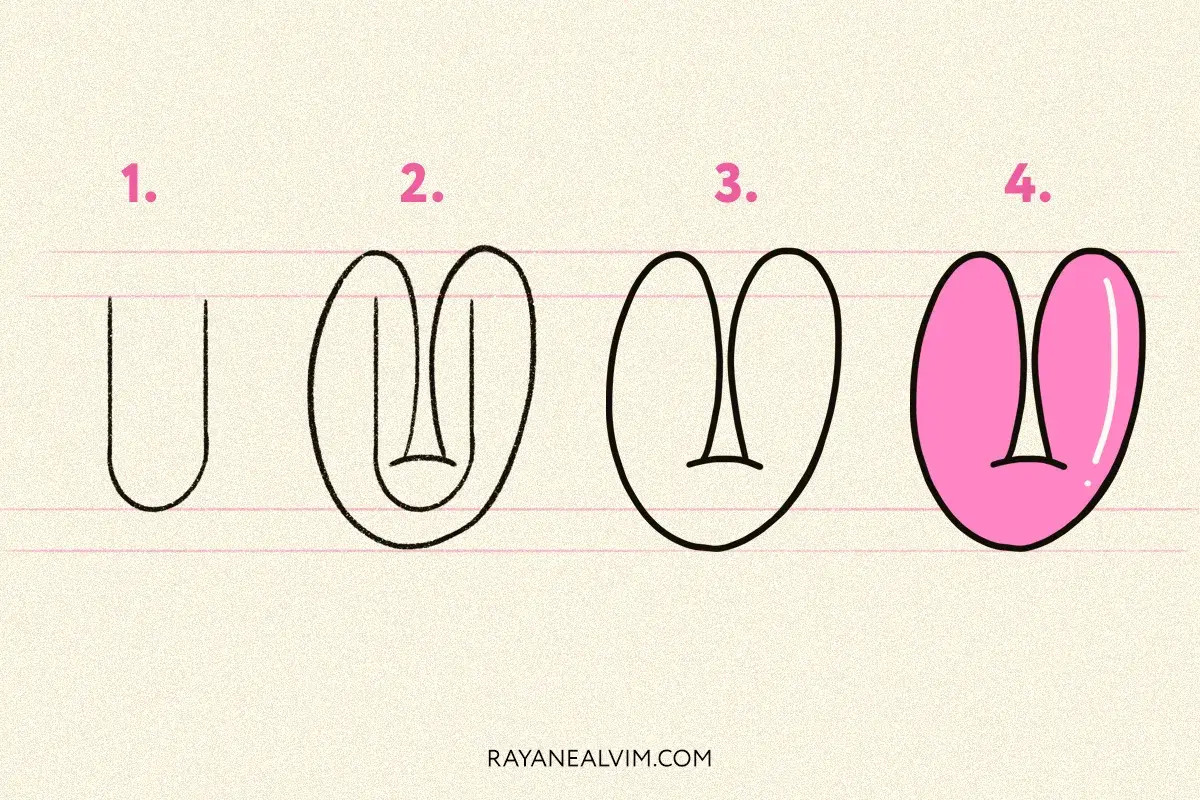
La U mayúscula parece una letra sencilla, pero en tipografía y lettering cambia mucho según el trazo, el contraste y el contexto. Su forma puede verse sobria, amable, geométrica o muy decorativa, y eso afecta tanto a la legibilidad como al carácter visual de un cartel, una etiqueta o un monograma. Aquí voy a explicarte qué la hace especial, cómo dibujarla con buen equilibrio y qué detalles conviene cuidar para que funcione de verdad en diseño.
Lo esencial para entender la U en mayúscula
- La U es la vigesimosegunda letra del abecedario español y la quinta vocal.
- Su silueta es muy flexible: cambia bastante entre tipografías serif, sans, script y display.
- La mayúscula no elimina los signos diacríticos: Ú y Ü se escriben cuando corresponden.
- En diseño creativo funciona muy bien como inicial, monograma, rótulo o letra protagonista.
- El error más común no es decorarla poco, sino hacerla perder aire interior y claridad.
Qué aporta la U mayúscula al abecedario visual
La RAE la sitúa como la vigesimosegunda letra del abecedario español y la quinta vocal. Más allá del dato, a mí me interesa su comportamiento visual: es una letra abierta, estable y fácil de reconocer incluso a distancia. Por eso encaja tan bien en títulos, nombres propios y piezas donde una sola inicial tiene que sostener bastante presencia sin parecer pesada.
También tiene algo muy útil para cualquier proyecto creativo: no depende tanto de adornos para funcionar. Una U bien construida ya transmite orden, redondez y equilibrio. Cuando la letra está bien resuelta, el resto del diseño respira mejor; cuando está mal resuelta, el conjunto suele verse torpe aunque el color o la composición sean correctos. Esa diferencia explica por qué conviene tratarla con más atención de la que suele recibir. Con esa base, el siguiente paso es ver cómo cambia según el estilo tipográfico.
Cómo cambia su forma según el tipo de letra
No hay una sola U correcta. Yo suelo pensar en ella como una estructura base que cada familia tipográfica interpreta de otra manera. En unas letras la curva inferior es suave y casi ceremonial; en otras, la forma es más geométrica y rotunda; en otras, la U se vuelve fluida y se enlaza con otras letras. Esa variación no es un capricho: responde al tono de la pieza y al tamaño en el que se va a leer.
| Estilo | Cómo suele verse la U | Cuándo conviene |
|---|---|---|
| Serif | Contraste suave, remates en los extremos y una base más clásica. | Invitaciones, libros, identidad elegante y piezas con aire editorial. |
| Sans serif | Contorno limpio, curvas homogéneas y lectura muy directa. | Señalética, infografías, marcas modernas y textos breves. |
| Script o caligrafía | Entrada y salida fluidas, trazos variables y posible unión con otras letras. | Firmas, láminas decorativas, bodas y proyectos de lettering manual. |
| Display | Proporciones libres, cortes, sombras, volumen o recursos expresivos. | Portadas, pósteres, vinilos y composiciones donde la letra sea protagonista. |
Lo que yo vigilo siempre es el hueco interior. Si la contraforma se cierra demasiado, la U pierde respiración y se vuelve más pesada de lo necesario. Cuando la letra conserva ese aire interno, resulta más limpia y también más versátil, tanto en pantalla como en papel. Con esa idea clara, ya tiene sentido pasar al trazo manual y ver cómo se construye sin perder equilibrio.
Cómo dibujarla a mano sin que pierda equilibrio
Cuando la dibujo a mano, empiezo por un eje imaginario y por la altura total antes de añadir cualquier adorno. La U agradece una construcción limpia: dos laterales casi paralelos y una base redondeada que no quede ni demasiado puntiaguda ni demasiado ancha. Si la base aprieta, la letra se encoge visualmente; si se abre demasiado, se desarma.
Marca la altura y el ancho
Primero fijo la altura de las dos astas laterales y decido cuánto espacio tendrá el interior. En lettering, esa decisión manda más de lo que parece. Una U muy estrecha transmite tensión; una demasiado abierta puede parecer vacía. Yo suelo probar dos o tres versiones rápidas antes de quedarme con una.
Cierra la base con una curva continua
La parte inferior funciona mejor cuando el gesto es fluido. No me interesa que la curva parezca un ángulo redondeado improvisado, sino una transición limpia entre ambos laterales. Si trabajo con rotulador o brush pen, busco que el movimiento de entrada y salida tenga la misma intención para que la letra no cojee hacia un lado.
Ajusta el contraste según la herramienta
Con un pincel o un brush pen, la presión natural ya da contraste entre trazos finos y gruesos. Con un rotulador plano, en cambio, hay que cuidar mucho el giro de la mano para que los laterales no queden descompensados. En una pieza pequeña, además, conviene simplificar: cuanto más fina sea la letra, más fácil es que se pierda al reducirla.
- Revisa el espacio lateral cuando la coloques junto a otras letras redondeadas o muy verticales.
- Si es decorativa, conserva siempre una ruta de lectura limpia en el contorno.
Cuando una U está bien pensada, deja de ser una vocal más y pasa a actuar como una pieza de equilibrio dentro del diseño. Esa es la parte interesante: una letra aparentemente simple puede cambiar por completo la sensación de un cartel, una portada o una manualidad si respetas su aire interno, sus signos y su relación con el resto de la composición.